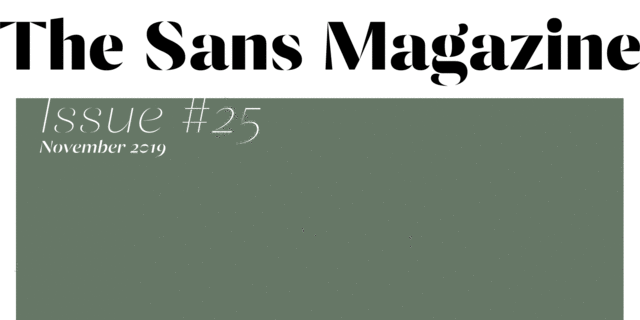
Ponzu – элегантный акцидентный трафаретный шрифт без засечек. Его форма определяется острыми окончаниями штрихов, которые исчезают в бесконечном контрасте, приближаясь к основному штриху. Это гибридный шрифт с красивыми каплевидными элементами, типичными для антикв. Он идеально подходит для акцидентного использования в редакционных целях, для брендинга, постеров, экранных приложений и т. д. Ponzu поставляется в 9 насыщенностях со стильным курсивом для каждого прямого начертания. Поддерживает множество языков, включая кириллицу, и содержит OpenType фичи. Шрифт разработал и выпустил Андрей Константинов в студии Mint Type в 2019 году.